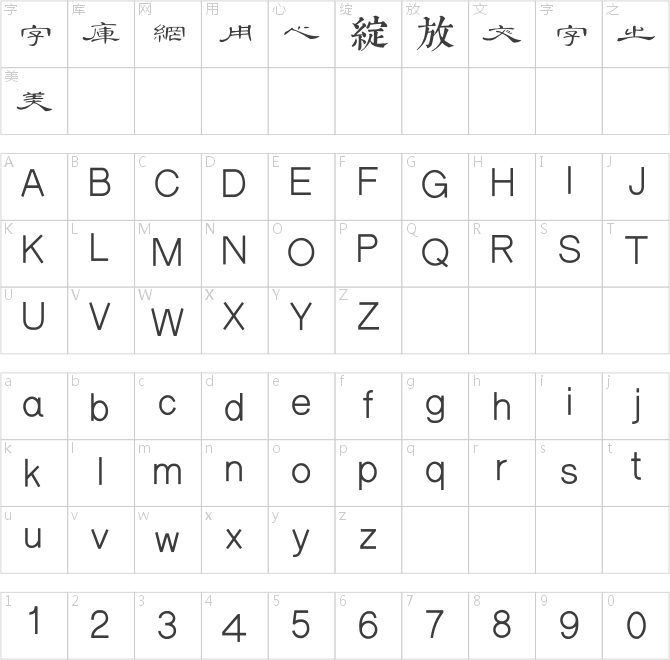
邯鄲席夔隸書千字文
邯鄲席夔隸書千字文字體下載邯鄲(清)席夔隸書千字文
席夔,字梧川,唐朝書法家,詩人。貞元十年進士及第,十二年博學宏詞及第。
邯鄲席夔隸書千字文字體邯鄲(清)席夔隸書千字文字庫是一款讓人賞心悅目、百看不厭的中文字體,適合各類廣告和產品包裝設計應用,字體大小6.45MB,格式為ttf字體,上傳用戶是邯鄲字庫,作者/版權方為韓紹杰